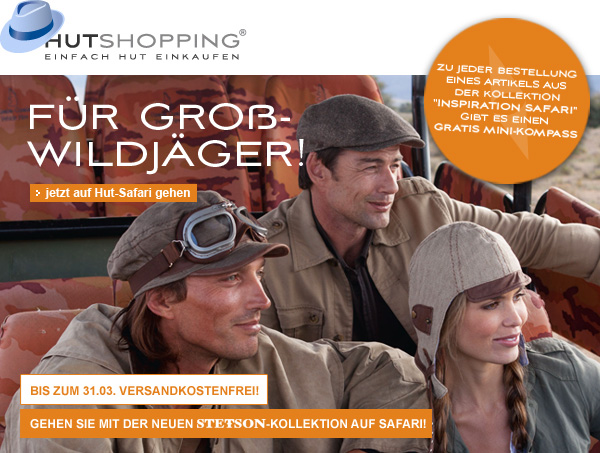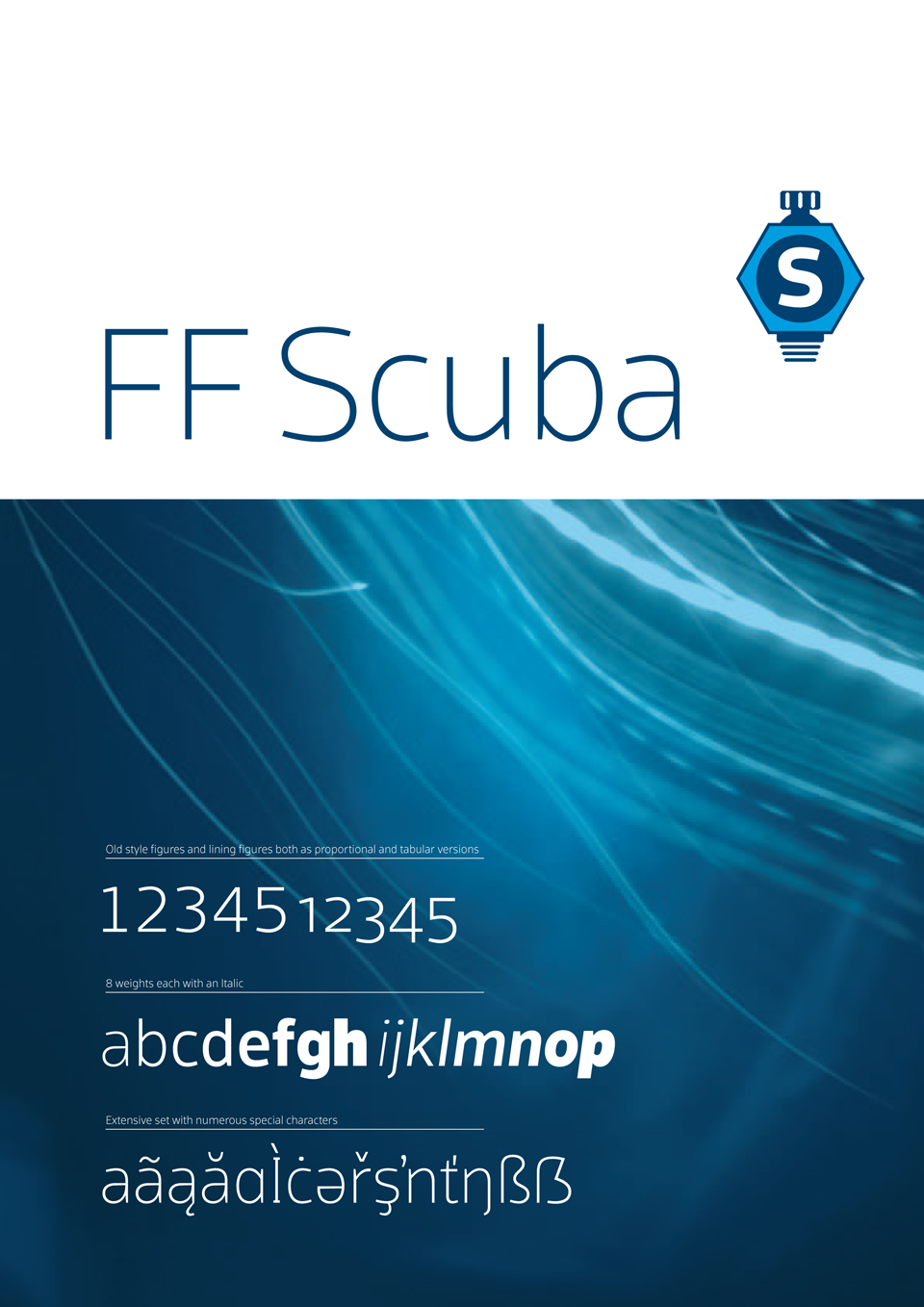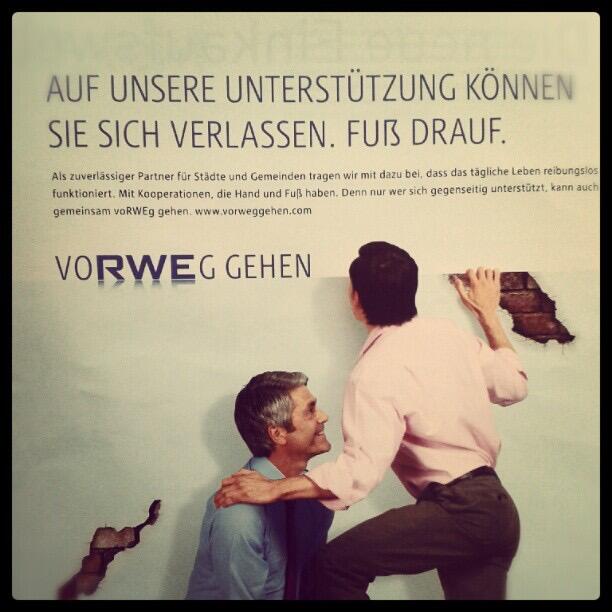
Was macht eigentlich die Bundesdruckerei mit ihren Schriften? Haben die auch inzwischen ein Versal-Eszett für die Personalausweise?
Deshalb das Fragezeichen. In meinem Bild wurde das nicht so deutlich, zumal die Strichstärke stimmt, nur der Überstand oben hat mich gestört. Und die Form natürlich. Aber ein kleiner, wenn auch aus fachmännischer Sicht nicht gelungener Beitrag dazu, das [sZ][/sZ] in den Sehnerv der Allgemeinheit zu tätowieren.
Warum baut man eigentlich in die Fonts keine Intelligenz ein, so dass ein ß zwischen zwei Grossbuchstaben automatisch als grosses Eszet angezeigt wird? Zugegeben, in diesem Fall hätte das wohl nicht geholfen, von wegen dummen Programmen und so, aber das wäre doch eine Lösung für die Zukunft.
Weil das von einem dummen (hier bitte irgend einen Beruf einsetzen) von Hand in ein kleines ß korrigiert wird.
Das widerspräche ja den geltenden Mapping- und Rechtschreibregeln, die du ja so gerne anführst.
Gute Antwort! Allerdings ist es ja auch nicht so, dass eine Eingabe wie DRAUßEN automatisch umgewandelt würde zu DRAUSSEN (wie es den gültigen Regeln entspräche). Eine automatische Umwandlung zu DRAUẞEN würde vielleicht der Absicht besser entsprechen, wenn man schon extra ein (nicht regelkonformes) Eszet tippt.
Für Wörtern wie GROß müsste die automatische Ersetzungsregel anders formuliert werden: Zeige ein ß als ẞ an, wenn zwei Grossbuchstaben vorangehen. Wörter wie blieben unerfasst, aber es lässt sich halt nicht jedes Problem automatisch lösen.
Das wirkt irgendwie sehr als hätte das jemand dazu gebastelt. Oder ist das doch eine Minuskel :-?
Also ich lese da Grobwildjäger. Vielleicht hieß die Grobe Mettwurst früher auch mal GROßE METTWURST … :-)
Ich habe spontan schon ein ẞ gelesen, aber ich finde, es harmoniert nicht so richtig gut mit den übrigen Zeichen. Es wirkt einen Hauch zu schmal und irgendwie auch einen Hauch zu niedrig. Oder? :-?
Das ist ein kleines, würde ich sagen. Aber das ist eben das Problem: auch wenn Mach es harmonisch finden mag, wenn kleines und großes gleich oder ähnlich aussehen – das bezieht sich dann eben aufs »Betrachten« und nicht aufs »Lesen«. Ein ß ist dieser Gestaltung wird eben im Versal-Satz zu einem B – die Lücke links unten macht das B dann zwar zu einem seltsamen B, aber eben nicht automatisch zu einem Versal-Eszett. Dazu muss man es schon strukturell anders gestalten.
Mir fällt gerade ein: Genau dieses ß haben wir hier schon mal an anderer Stelle diskutiert. Es ist die Aviano Sans und es ist definitiv das kleine ß, ein großes gibt es nämlich nicht.
Na ja, der Huthändler hat ja nicht die Schrift (und damit das Versal-ß) entwickelt. Die Verwechslungsgefahr mit dem B hätte ich jetzt auch nicht gesehen, es passt aber m. E. vom Charakter her nicht zum Rest.
Das ist ein kleines, würde ich sagen. Aber das ist eben das Problem: auch wenn Mach es harmonisch finden mag, wenn kleines und großes gleich oder ähnlich aussehen – das bezieht sich dann eben aufs »Betrachten« und nicht aufs »Lesen«. Ein ß ist dieser Gestaltung wird eben im Versal-Satz zu einem B – die Lücke links unten macht das B dann zwar zu einem seltsamen B, aber eben nicht automatisch zu einem Versal-Eszett. Dazu muss man es schon strukturell anders gestalten.
:-) Wenn kleines und grosses Eszet harmonisch aufeinander abgestimmt sind – so wie ich es gerne mag –, so hat das durchaus nichts mit der Verwechselbarkeit des grossen B zu tun. Zwei Paar Schuhe. Auch bei einem grossen Eszet, das strukturell anders gestaltet ist als ein kleines Eszet, kann Verwechslungsgefahr mit dem grossen B bestehen. Es ist sogar, denke ich, nicht nur eine Frage der Gestaltung, sondern auch eine Frage der Lesegewohnheit. Die Gefahr der Verwechslung lässt sich nur dann mit Sicherheit ausschliessen, wenn man sich an die Rechtschreibung hält und SS schreibt.
Bei WDRs Wissen macht Ahh! bzw. Mini Ahh wird dezent über das große Eszett geschwiegen. Kein wunder das sich das nicht durchsetzt, wenn’s beim Bildungsfernsehn keiner weiß, dass es eins gibt ;-)
Habe ich eben auch gesehen und mich darüber geärgert...